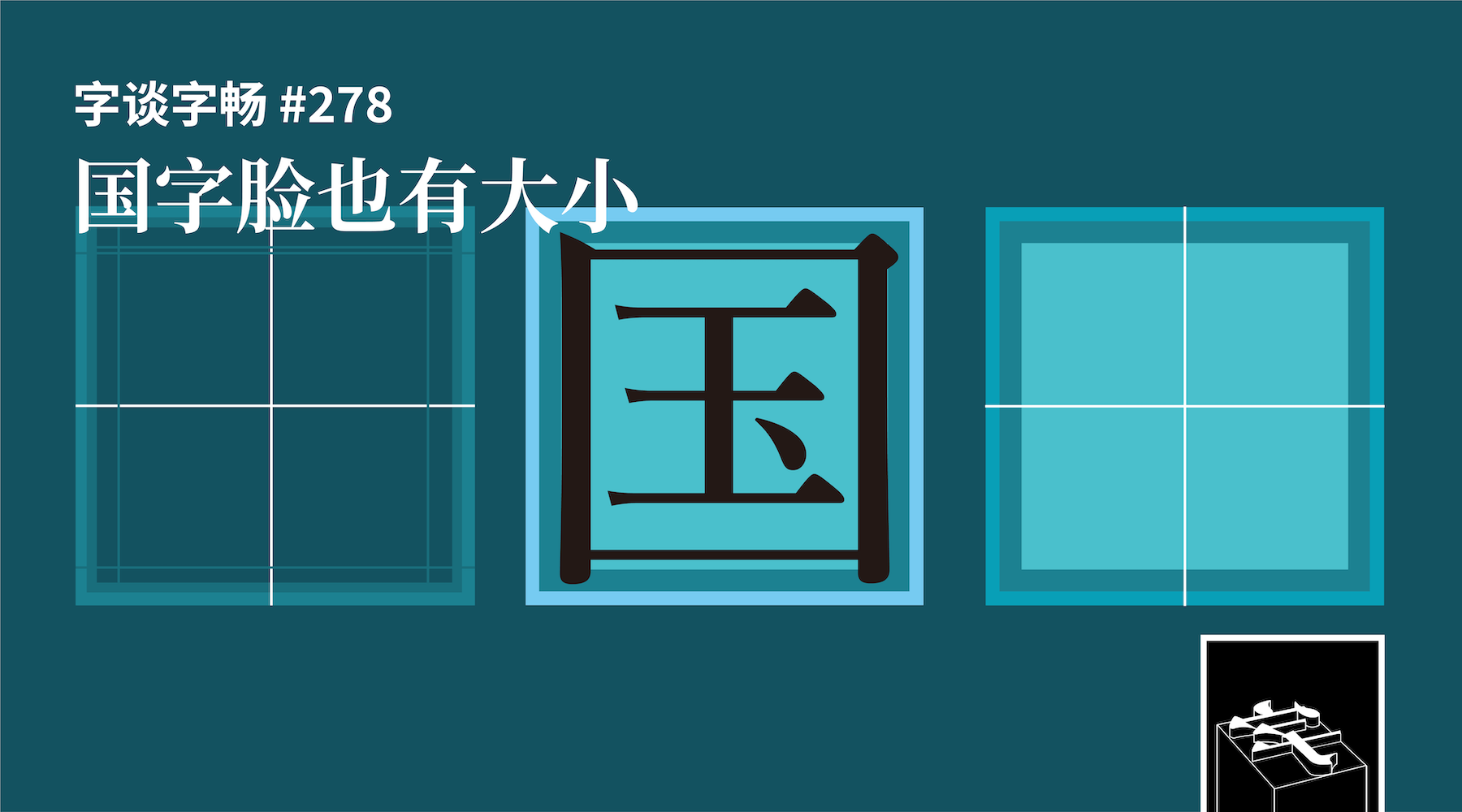
今天的嘉宾依然是老朋友厉致谦。本期节目,我们将探讨中文字体设计的另一重要概念——字面。同时,老厉也将与我们分享上海印研所的前辈们,对于这一概念的认知、研究及运用。
- 徐學成(著).厲致謙、應寧(編著).《字耕一生:徐學成的故事》.三聯書店(香港)有限公司,2026 年
- 日文字体设计中的「字面」概念
- 徐学成,字体设计师,早年于上海印刷技术研究所工作;「汉字印刷字体书写技艺」(上海市非物质文化遗产项目)代表性传承人
- 「徐学成字体设计回顾展」线上展览及档案
- 齐立,字体设计师,曾任职于上海印刷技术研究所字体研究室、方正字库、汉仪字库等;代表作有方正倩体系列、微软雅黑/方正兰亭黑、方正兰亭宋、汉仪旗黑等
- 鳥海修.『明朝体の教室』.Book & Design,2024 年
- 乔进安,华丰印刷铸字所乔雨亭之子,长期担任上海字模一厂厂长及上海印刷研究所顾问
- 英丝(mil/thou),千分之一英寸
- 方正飞翔、方正书版等软件中有针对其自家字体的「字心字身比」功能
- Adobe InDesign 的「字符对齐方式」设置
- OpenType 字体格式规范中定义的汉字「平均字面」(ICF,Ideographic Character Face)
- OpenType 字体格式规范的「基线表」(BASE)中,设置了用于记录各种字体度量数值的标签,其中包括记录汉字字面信息的
icfb与icft标签 - 厉致谦所撰《「中文字体解秘组计划」第一阶段成果》,2025 年刊于 The Type